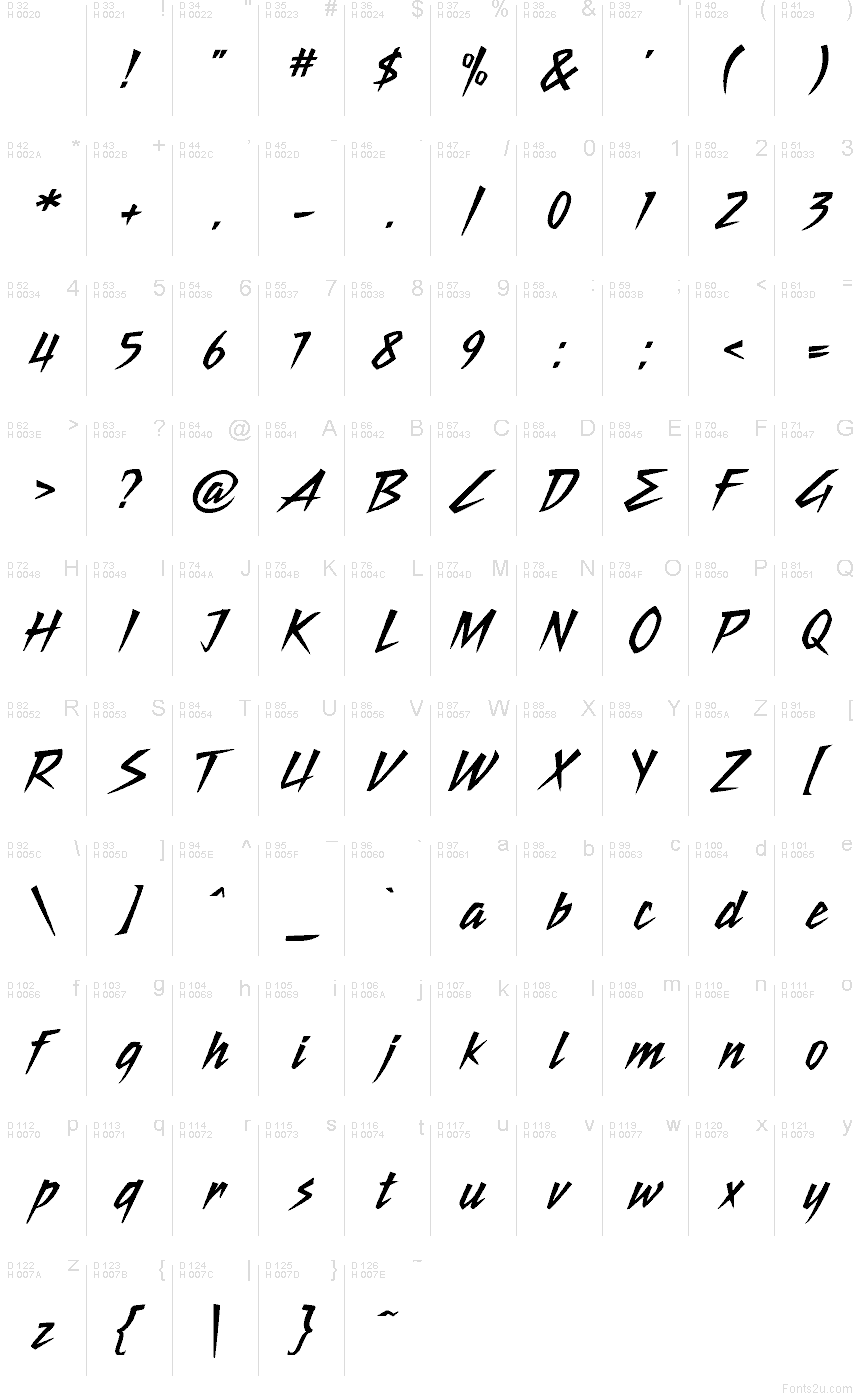
Electro Garden
Electro Garden, un font script a pennello gratuito di Cat.B, ha un carattere veloce ed elettrico che unisce una lettera iniziale spigolosa a tratti fluidi e connessi. Le lettere sono inclinate in avanti, con gesti spessi, intrisi d'inchiostro e tagli netti, dando al font un'aria che ricorda sia il lettering urbano che una firma rapida, con quel pizzico di grinta che serve per non risultare mai troppo morbido.
È quindi perfetto per poster musicali, copertine di fanzine, grafiche per skate, branding di moda e cartelli, dove un font gratuito deve trasmettere movimento più che perfezione. Funziona benissimo anche per titoli brevi o logotipi audaci, perché il ritmo tagliente e le giunzioni a gancio donano anche a poche lettere un battito energico e autenticamente disegnato a mano.